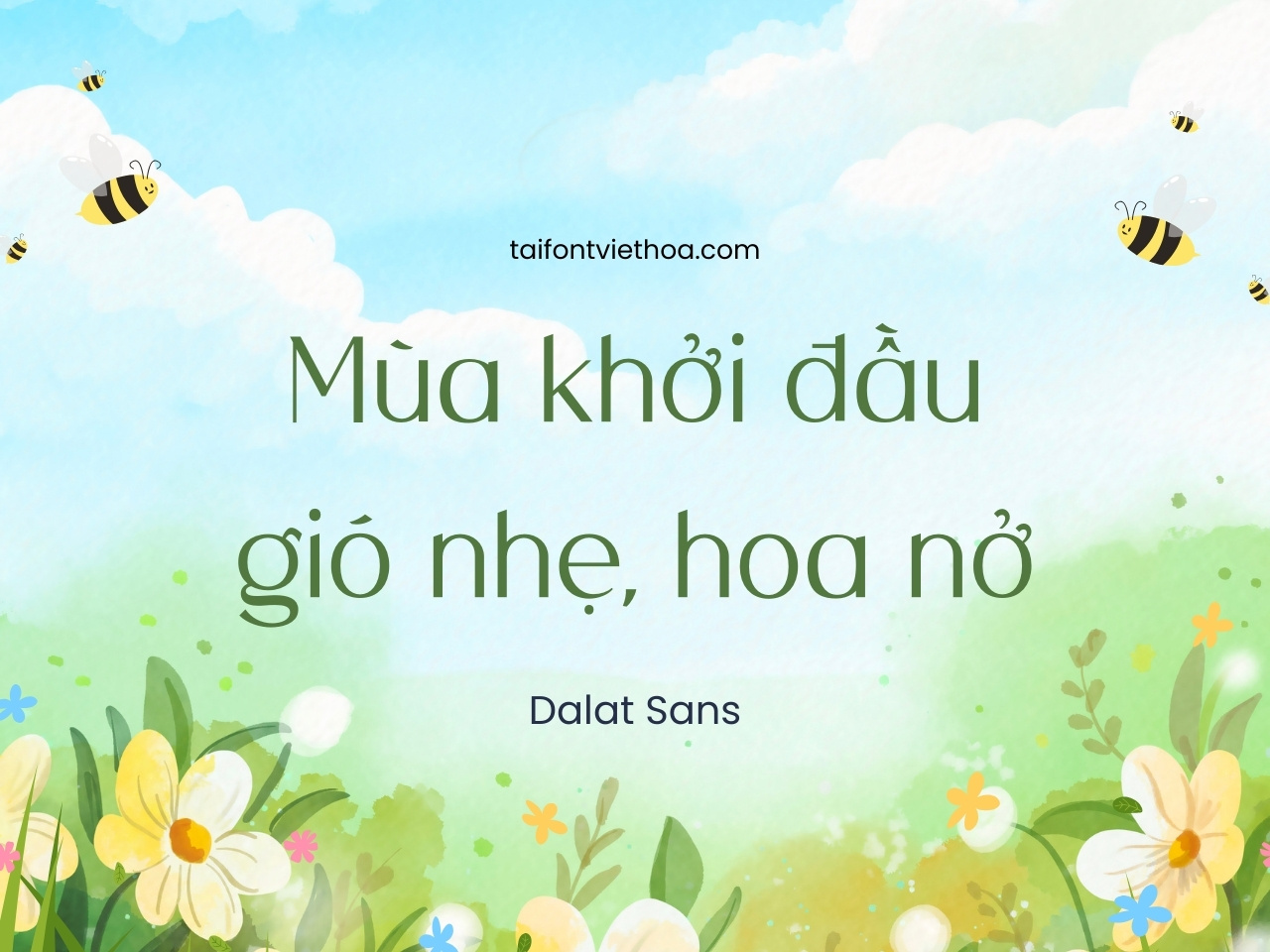
Giới thiệu về font Dalat Sans và phiên bản Việt hóa
Dalat Sans là một bộ font chữ không chân (sans-serif) được thiết kế bởi Mack Trinh – nhà thiết kế người Việt với cảm hứng từ vẻ đẹp hiền hòa, thanh lịch của thành phố Đà Lạt. Bộ font gồm hai phiên bản chính: Dalat Sans thường và Dalat Sans Cap (viết hoa toàn bộ), phù hợp cho nhiều mục đích trình bày khác nhau. Với tinh thần hiện đại, tối giản và đậm chất địa phương, Dalat Sans đã nhanh chóng thu hút giới thiết kế Việt yêu thích kiểu chữ sans truyền cảm.
Bộ font được Việt hóa hoàn chỉnh bởi chính tác giả Mack Trinh, hỗ trợ đầy đủ tiếng Việt chuẩn Unicode, cùng khả năng tương thích với hơn 70 ngôn ngữ khác dựa trên bảng chữ Latin mở rộng. Font Dalat Sans không chỉ là sản phẩm thiết kế mà còn là tâm huyết cá nhân trong việc xây dựng bản sắc địa phương thông qua ngôn ngữ thị giác. Font đã được taifontviethoa.com sưu tầm, kiểm duyệt và chia sẻ lại với mong muốn đưa sản phẩm sáng tạo Việt đến gần hơn với cộng đồng thiết kế chuyên nghiệp.
Đặc điểm thiết kế nổi bật và các ứng dụng tiêu biểu
Dalat Sans sở hữu cấu trúc chữ sans-serif gọn gàng, đường nét tròn trịa, đều đặn với khoảng cách ký tự được cân chỉnh tỉ mỉ. Đặc biệt, phiên bản Dalat Sans Cap sử dụng toàn bộ chữ viết hoa, tạo cảm giác mạnh mẽ và nổi bật trong các tiêu đề, bảng hiệu hoặc khẩu hiệu. Cả hai biến thể đều dễ đọc, thích hợp với thiết kế hiện đại, tối giản hoặc mang hơi hướng công nghệ.
Font Dalat Sans phù hợp cho các ứng dụng như thiết kế thương hiệu, bao bì sản phẩm, giao diện website, đồ họa kỹ thuật số, bất động sản, công nghệ hoặc quảng cáo ngoài trời. Với tinh thần tươi trẻ và sáng tạo, font này có thể phục vụ cho cả dự án cá nhân lẫn chiến dịch truyền thông doanh nghiệp.